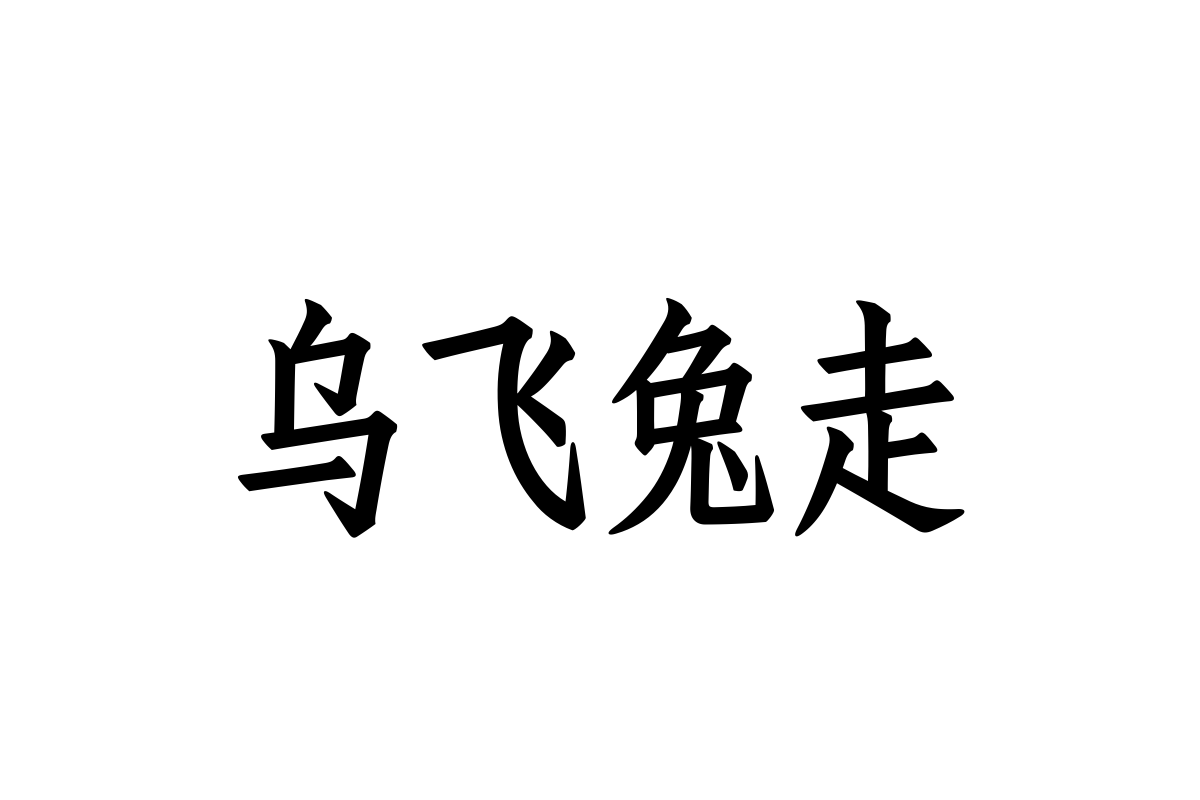
汉仪英雄仿宋简体是一款具有现代感和简洁风格的字体。它由汉仪公司设计,旨在为用户提供一种易于阅读、美观的字体选择。这款字体以其清晰的线条和优雅的字形而受到广泛欢迎。
汉仪英雄仿宋简体的特点如下:
1. 清晰易读:字体线条流畅,字形规整,使得文本内容易于阅读和理解。
2. 现代感:该字体采用简洁的设计,符合现代审美趋势,适合各种场合使用。
3. 适应性强:适用于各种印刷媒介,如报纸、杂志、广告、包装等。
总之,汉仪英雄仿宋简体是一款实用的字体,适用于各种需要清晰、易读、美观文字的场景。